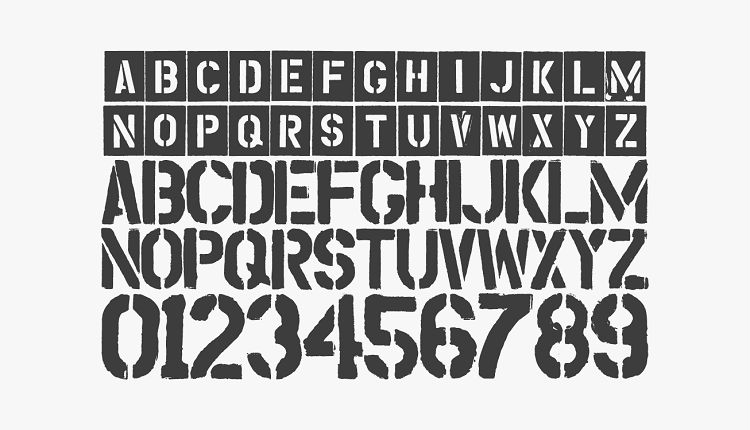
Шрифты в полиграфии
Шрифт имеет огромное значение при разработке дизайн-макетов. Его задача – передать информацию, от него зависит то, как информация будет воспринята.
Принято считать, что шрифт – это комплект графических знаков какой-либо системы письма. По наклону различают прямой, курсивный и наклонный шрифт; по насыщенности – светлый, полужирный, жирный. Существуют и другие виды классификации – по размеру ширины и высоты, характеру рисунка, назначению и т.д.
Особенности рисунка знаков складываются исторически, с их учётом подбирают шрифт для конкретного вида литературы, например, научной или художественной.
- книжные,
- газетные,
- плакатно-афишные,
- картографические,
- декоративные,
- рекламные,
- для документов строгой отчётности.
К шрифтам предъявляют определённые требования:
- эстетическое (шрифт должен быть красивым),
- экономическое (удовлетворительное среднее число знаков, размещаемых в одной строке),
- технико-технологическое (точность печати различными методами),
- гигиеническое (шрифт должен восприниматься как можно быстрее, с минимальным утомлением).
Решением задачи оптимального восприятия текста занимается типографика. Именно с этим искусством связан шрифтовой дизайн и оформление книг.
Как подобрать шрифт?
Высокая чёткость шрифта позволит читателю легко отличать символы друг от друга. Высокий уровень читаемости обеспечивается несколькими параметрами – и шириной полосы, и стилем изложения, и написанием текста.
Типографика считает шрифт читаемым, если он знаком читателю, имеет крупный размер и размещен в строке умеренной длины, а контраст между текстом и бумагой достаточно высок. При этом текстура бумаги не должна мешать восприятию.
Не рекомендуется использовать только прописные буквы – такой текст читается дольше и, кроме того, занимает больше места. Курсив сложно читать, так же, как очень длинные или очень короткие строки. Шрифты старого стиля хорошо сочетаются с грубой бумагой, а современные – с гладкой.
Развитие шрифтов
В начале своего развития шрифты были очень схожи с каллиграфическим письмом стран, в которых они появились. Первые немецкие шрифты в 15-м веке имели резкие и жирные начертания, в то время как итальянские вполне соответствовали гуманистическому настрою того времени – были светлыми и изящными. Последние стали прародителями романских шрифтов.
Разработка новых начертаний шрифтовых знаков не останавливается. Компьютерные технологии значительно упростили и ускорили этот процесс.
Колоссальное количество шрифтов, разрабатываемых веками, являет собой мощнейший инструментарий для воздействия на целевую аудиторию, например, в рекламе. Обладание вкусом и достаточными знаниями в типографике позволят достичь желаемого результата.
Дима, расскажи про самое начало: про лихие 90-е, про запуск Esquire, про «Афишу» и про твои первые команды. Ты ведь вырос в редакциях, первый опыт, насколько я понимаю, именно журнальный?
Наверное, начать можно с «Афиши», она была той точкой, когда мы, познакомившись с Филиппом Бахтиным, решили идти против течения. Это был 2001 год, журнал «Большой Город». Мы хотели делать совершенно новую штуку, которая захватила бы всё: была читаема, популярна, цитируема.
В 2002-м, уволившись из «Афиши» после провала первой итерации «Большого Города», мы пошли с Данилкиным делать немецкий журнал Fit For Fun!, тоже пытаясь переделать его из дебильного журнала во что-то экологичное.
С чего началась история Esquire в России, что стало триггером?
В 2004-м Филя [Бахтин] позвал меня в журнал FHM, на который тогда купил лицензию издатель Михаил фон Шлиппе. На самом деле фон Шлиппе — это человек, который оказал на меня огромное влияние, давая мне драгоценную возможность делать то, что я считал нужным.
Филя ушёл из «Афиши», стал главарём, собрал себе команду из модников и красавиц. В какой-то момент он меня позвал на разговор вместе со Шлиппе. Это был зажигательный разговор. Я так, как сейчас, не умел разговаривать, я был грустный чувак, потому что у меня был хронический гастрит и я делал вещи, которые мне не нравились, и никакие блага не могли скомпенсировать это ужасное душевное неспокойствие. Разговор был о том, что «а давай-ка делать наконец то, что мы решили делать в Афише». То есть давай вместе сделаем офигенную штуку, которую все будут читать.
Знаешь, когда что-то интересное есть в голове, мы очень быстро стараемся это записать, чтобы не забыть. Как это происходит, когда мы пользуемся печатной машинкой? Наверное, очень быстро, сильно и уверенно бьём. Всё это влияет на оттиск, готовый печатный материал. Мы поняли, что всё это должно быть в шрифте на уровне вариативности букв. Когда ты поймал образ за хвост, начинаешь его быстро записывать — это очень грязные, вбитые в бумагу буквы. Внутри этого материала появляется сильнейшая вибрация. Всё дребезжит и кричит.